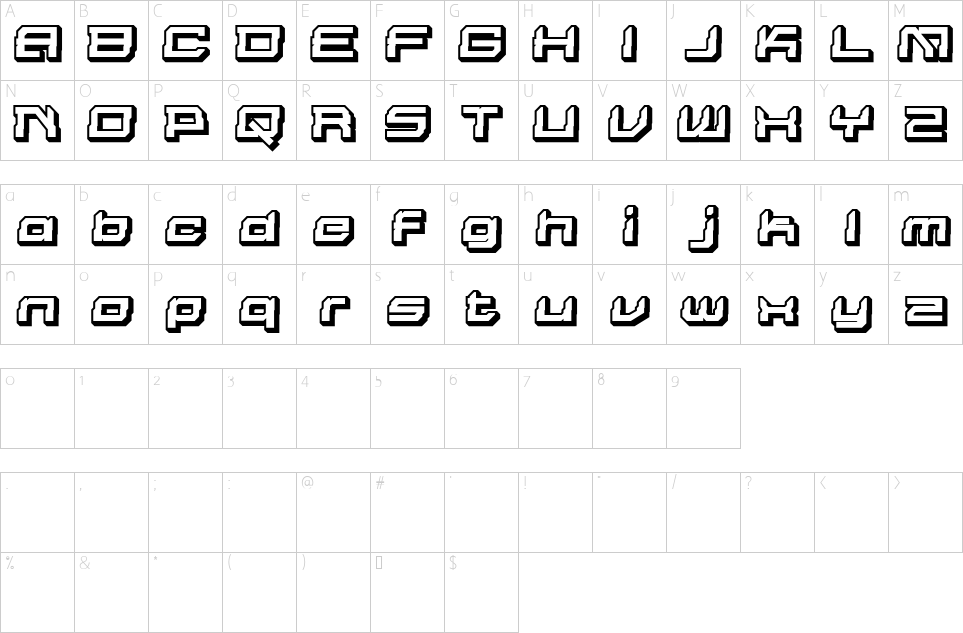
A Guinsa Font é uma opção gratuita para quem busca diversidade na tipografia do seu projeto no Windows ou Mac. Desenvolvida pela Craft Supply Co, esta font oferece um design elegante e sofisticado que se destaca entre os muitos recursos gráficos gratuitos disponíveis hoje. Com seus 1001 opções de fontes à disposição, a Guinsa Font é uma ótima escolha para designers e criativos em busca de diferentes estilos sem necessariamente precisar investir dinheiro extra. Com apenas um clique do seu lado, você pode adicionar esta font de alta qualidade ao seu próximo design ou projeto gráfico. Seja para o título, os detalhes ou até mesmo as legendas, a Guinsa Font é uma excelente escolha para aqueles procurando personalidade e originalidade em sua fonte de texto.